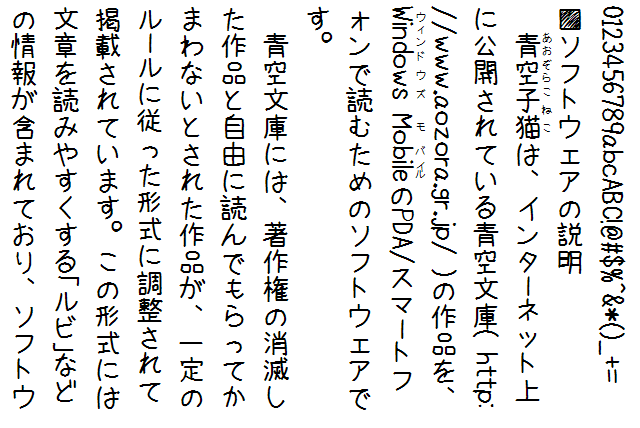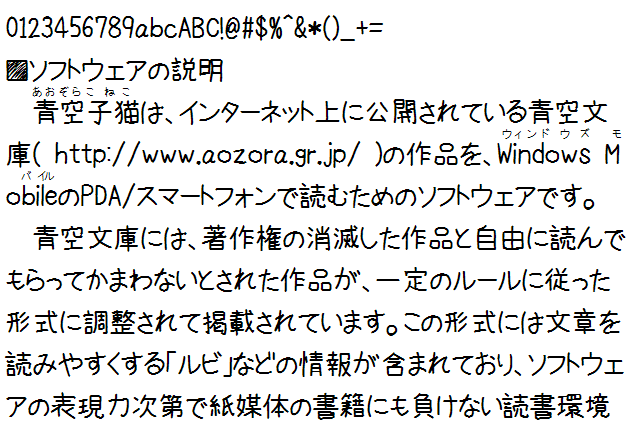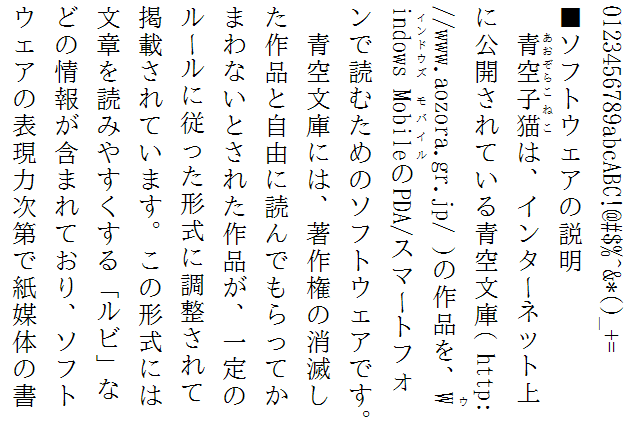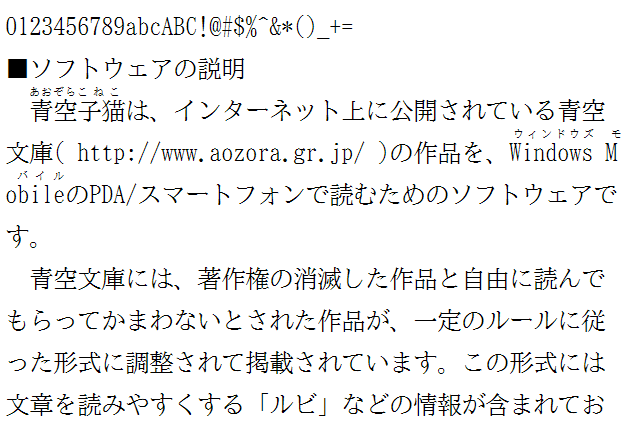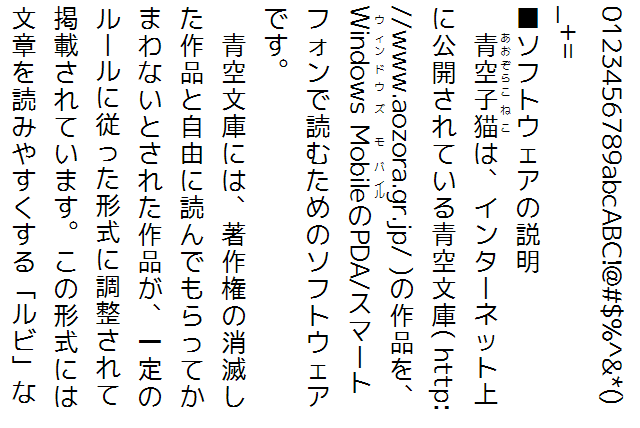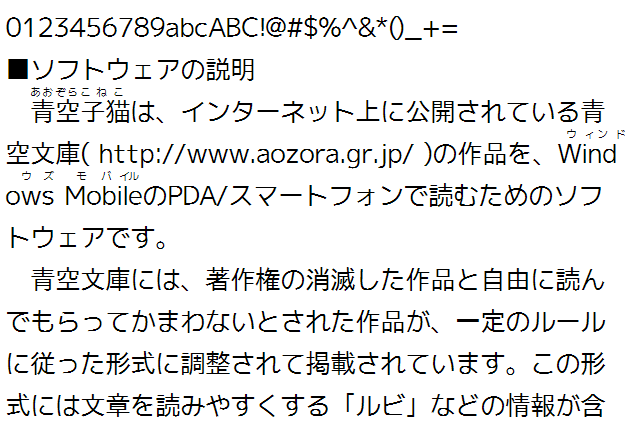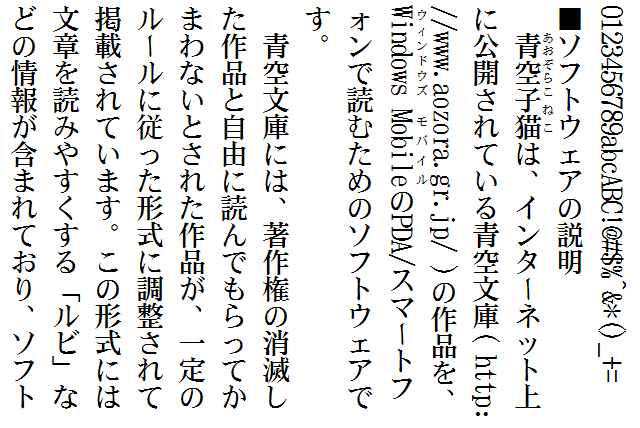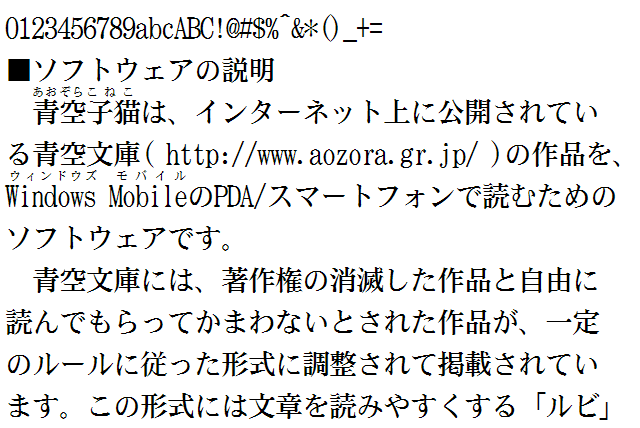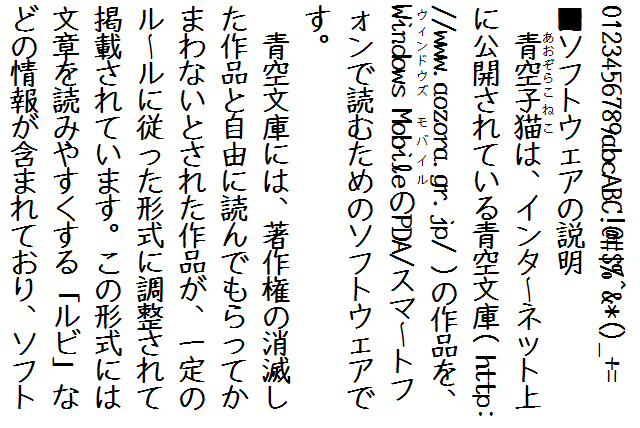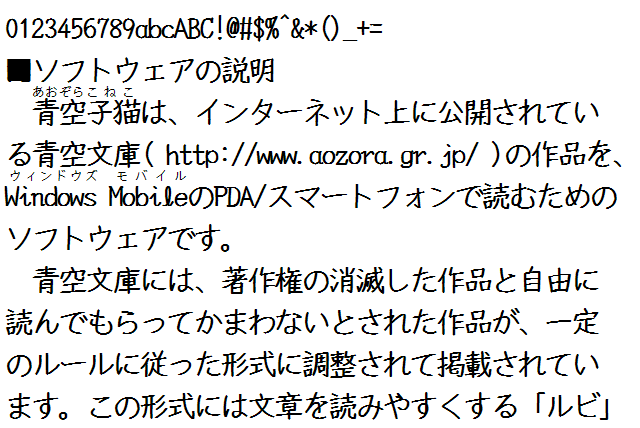
文章は、書体一つで印象が大きく変わります。
Windows Mobile に最初から内蔵されているフォントは、
・Courier New
・MS UI Gothic
・Tahoma
・MS ゴシック
・MS Pゴシック
の5書体で、日本語部分はいずれも同じ字形のゴシック体です。これだけではちょっと寂しいので、フリーで使えそうなフォントを探してみました。
■IPA(独立行政法人情報処理推進機構) TureTypeフォント付きGRASS国際化版
日本語での表示を行うために、IPAにより高品質なゴシック体・明朝体フォントが添付されて配布されています。
下のサンプルは、「IPA明朝(ipam.ttf)」です。
■M+ + IPA
「M+」というひらがなカタカナ英数の素敵なフォントをM+ FONTS PROJECT 森下浩司様が公開されていて、それにIPAの漢字書体を組み合わせたものをitouh@きりんシステム様が配布されています。
下のサンプルは、「M+フォント(ひらがな、カタカナ、英数字) + IPAゴシック(漢字)(M+1P+IPAG.ttf)」です。
■DFパブリフォント(ダイナコムウェア株式会社)
電子文庫パブリのユーザであればダウンロードができるようです。フリーのフォントではありませんので、取り扱いには注意が必要と思われます。太めの読みやすいフォントです。
下のサンプルは、「DFパブリW5D(DFPABURI.TTC)」です。
■Y.ozFONT
和文ペン字フォントで、JIS第1〜4水準が全て含まれています。手作りとは到底思えない素晴らしいフォントです。
下のサンプルは、「YOzB97E_.TTF」です。
■ほにゃ字
サウンドシアター「あらしのよるに」にも使われた、とても「ほにゃ」なかわいらしい文字です。JIS第1〜2水準をカバーしていますので、ラノベなテキストだといい感じに読めちゃうでしょう。
下のサンプルは、「HONYA-JI.ttf」です。